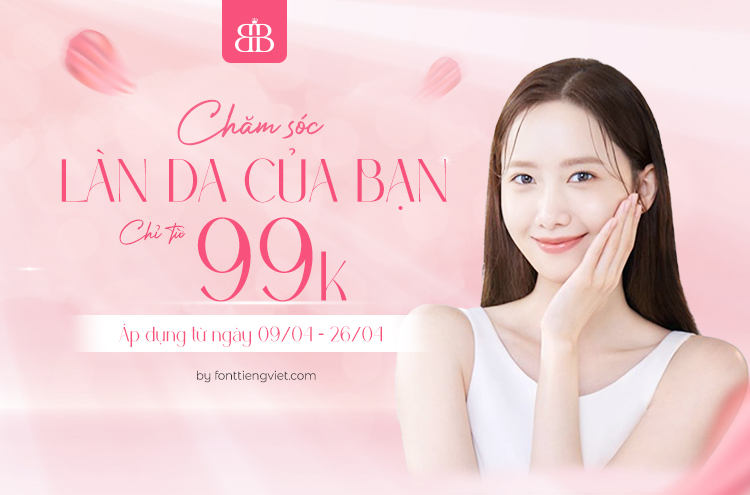
Combo font thiết kế Spa, Mỹ phẩm – Làm đẹp
Combo font thiết kế Spa, Mỹ phẩm – Làm đẹp: Bí quyết tạo nên vẻ đẹp sang trọng và đẳng cấp
Tầm quan trọng của Combo font thiết kế Spa, Mỹ phẩm – Làm đẹp trong nhận diện thương hiệu
Trong ngành công nghiệp thẩm mỹ và chăm sóc sức khỏe, ấn tượng đầu tiên đóng vai trò quyết định đến niềm tin của khách hàng. Việc lựa chọn Combo font thiết kế Spa, Mỹ phẩm – Làm đẹp phù hợp không chỉ giúp truyền tải thông điệp về sự chuyên nghiệp mà còn tạo dựng phong cách riêng biệt. Một bộ Font Miễn Phí chất lượng sẽ giúp các nhà thiết kế dễ dàng tạo nên những ấn phẩm truyền thông thu hút, từ logo, menu dịch vụ đến bao bì sản phẩm mỹ phẩm cao cấp. Khi kết hợp đúng các kiểu chữ, bạn sẽ tạo ra một tổng thể hài hòa, tôn vinh vẻ đẹp thanh lịch và tinh tế mà ngành làm đẹp luôn hướng tới.
Các tiêu chí lựa chọn font chữ cho ngành làm đẹp và spa
Sự thanh mảnh và uyển chuyển của font Serif
Các dòng font có chân (Serif) thường được ưu tiên hàng đầu trong các thiết kế mỹ phẩm. Những đường nét thanh mảnh, uốn lượn mang lại cảm giác sang trọng, quý phái và đáng tin cậy. Khi sử dụng trong Combo font thiết kế Spa, Mỹ phẩm – Làm đẹp, các font Serif giúp nhấn mạnh vào yếu tố di sản và chất lượng của thương hiệu. Điều này đặc biệt quan trọng đối với các dòng mỹ phẩm chăm sóc da cao cấp hoặc các dịch vụ spa trị liệu chuyên sâu, nơi khách hàng đòi hỏi sự tỉ mỉ và tận tâm trong từng chi tiết nhỏ nhất.
Sự hiện đại và tối giản của font Sans Serif
Ngược lại với Serif, các font không chân (Sans Serif) lại mang đến hơi thở hiện đại, trẻ trung và sạch sẽ. Trong thiết kế spa, các font này thường được dùng cho nội dung văn bản dài hoặc thông tin hướng dẫn sử dụng sản phẩm để đảm bảo sự dễ đọc. Một bộ font thiết kế chuẩn cần có sự cân bằng giữa nét cổ điển và hiện đại để phù hợp với xu hướng làm đẹp tối giản đang lên ngôi. Sự kết hợp này tạo nên một diện mạo mới mẻ, giúp thương hiệu dễ dàng tiếp cận với phân khúc khách hàng trẻ trung, yêu thích sự gọn gàng và tinh tế.
Cách phối hợp Combo font thiết kế Spa, Mỹ phẩm – Làm đẹp hiệu quả
Để tạo nên một bản thiết kế hoàn hảo, bạn không nên sử dụng quá nhiều kiểu chữ trong cùng một ấn phẩm. Quy tắc vàng là kết hợp một font chữ nghệ thuật (Script hoặc Serif) làm tiêu đề chính và một font chữ đơn giản làm nội dung bổ trợ. Việc lựa chọn Combo font thiết kế Spa, Mỹ phẩm – Làm đẹp đã được việt hóa giúp các designer tại Việt Nam tránh được lỗi hiển thị dấu tiếng Việt, đảm bảo tính thẩm mỹ cao nhất cho các chiến dịch marketing. Hãy chú ý đến khoảng cách giữa các chữ cái và độ dày của nét chữ để tạo ra khoảng trống thị giác, giúp người xem cảm thấy thư thái giống như đang trải nghiệm dịch vụ tại spa.
Kết luận về việc sử dụng font chữ trong ngành thẩm mỹ